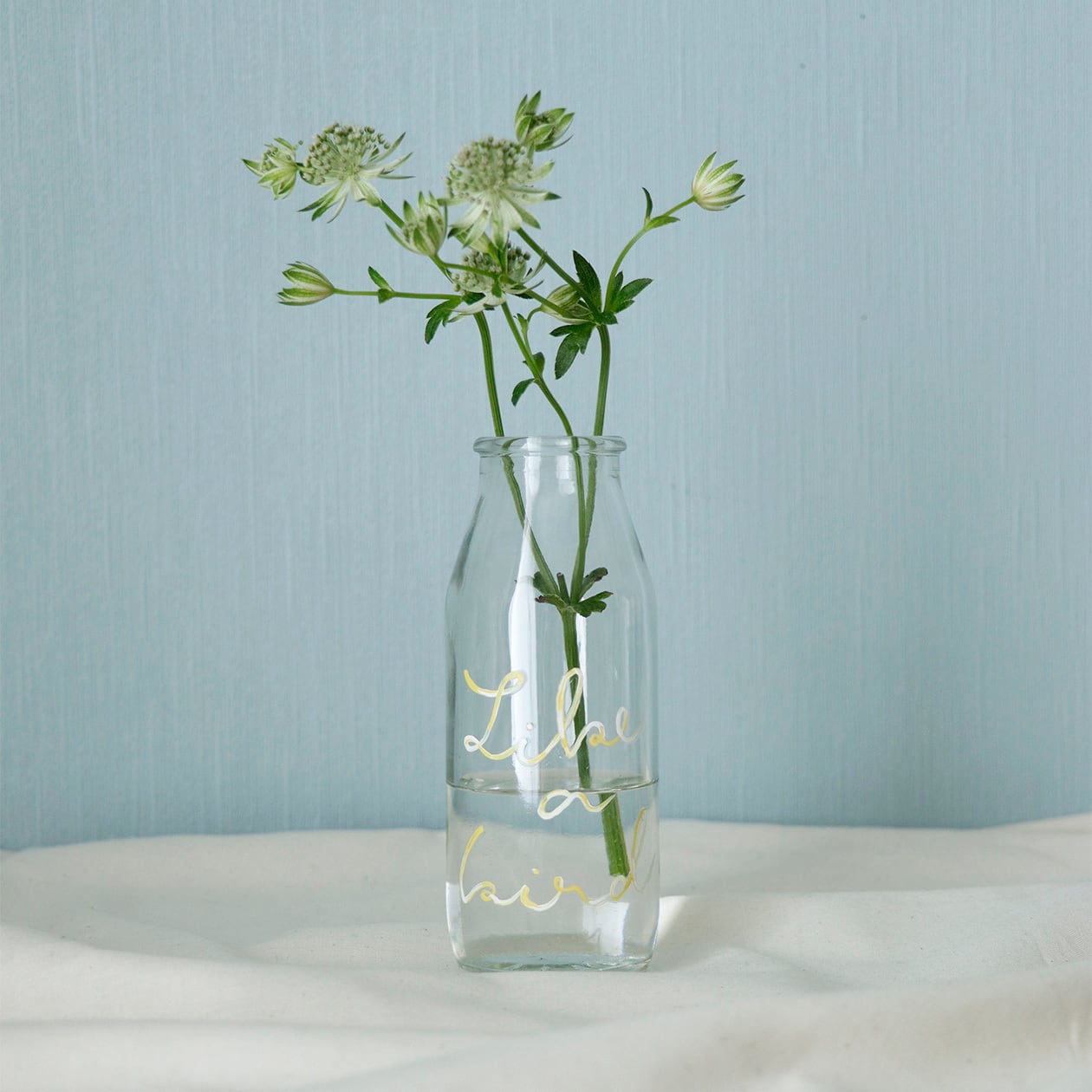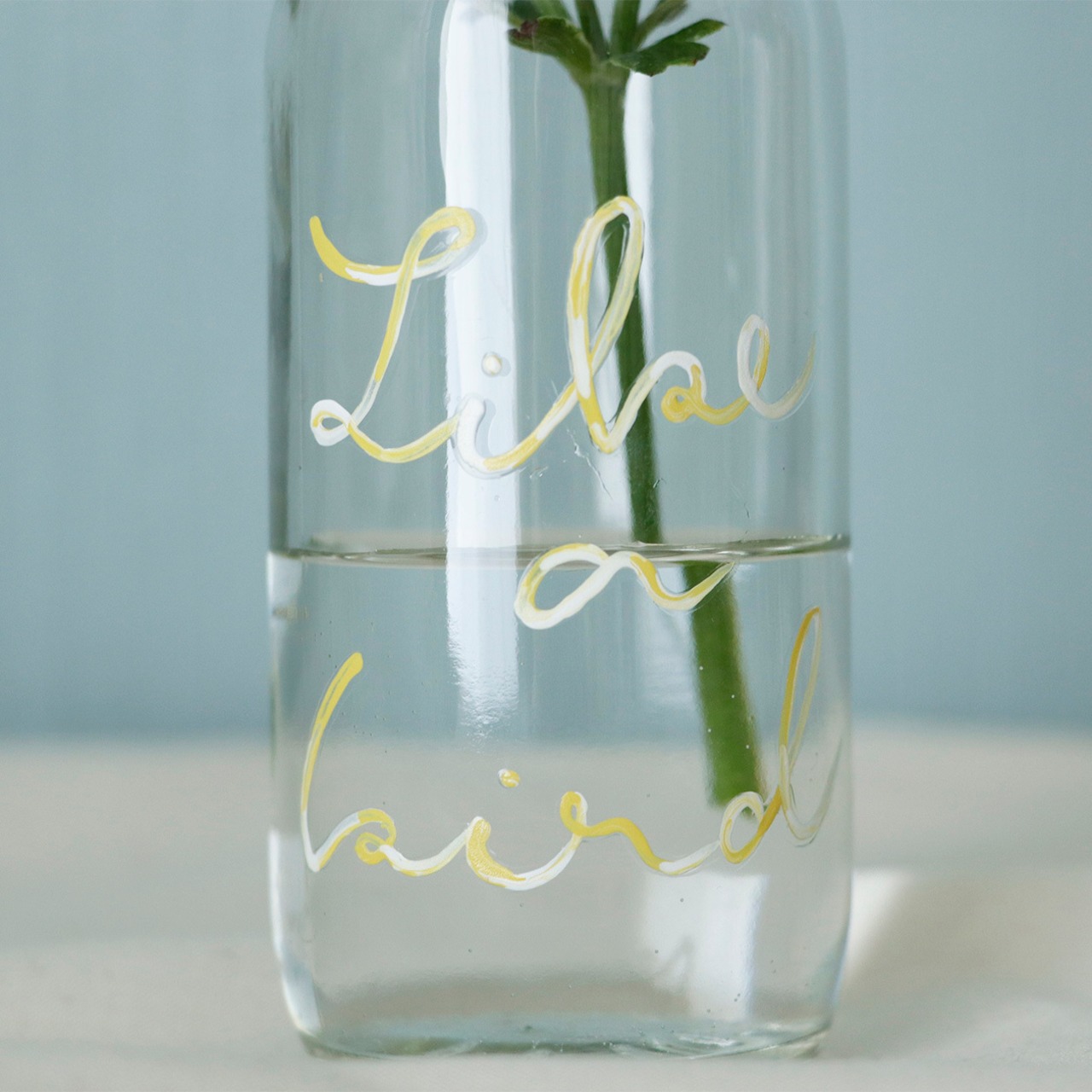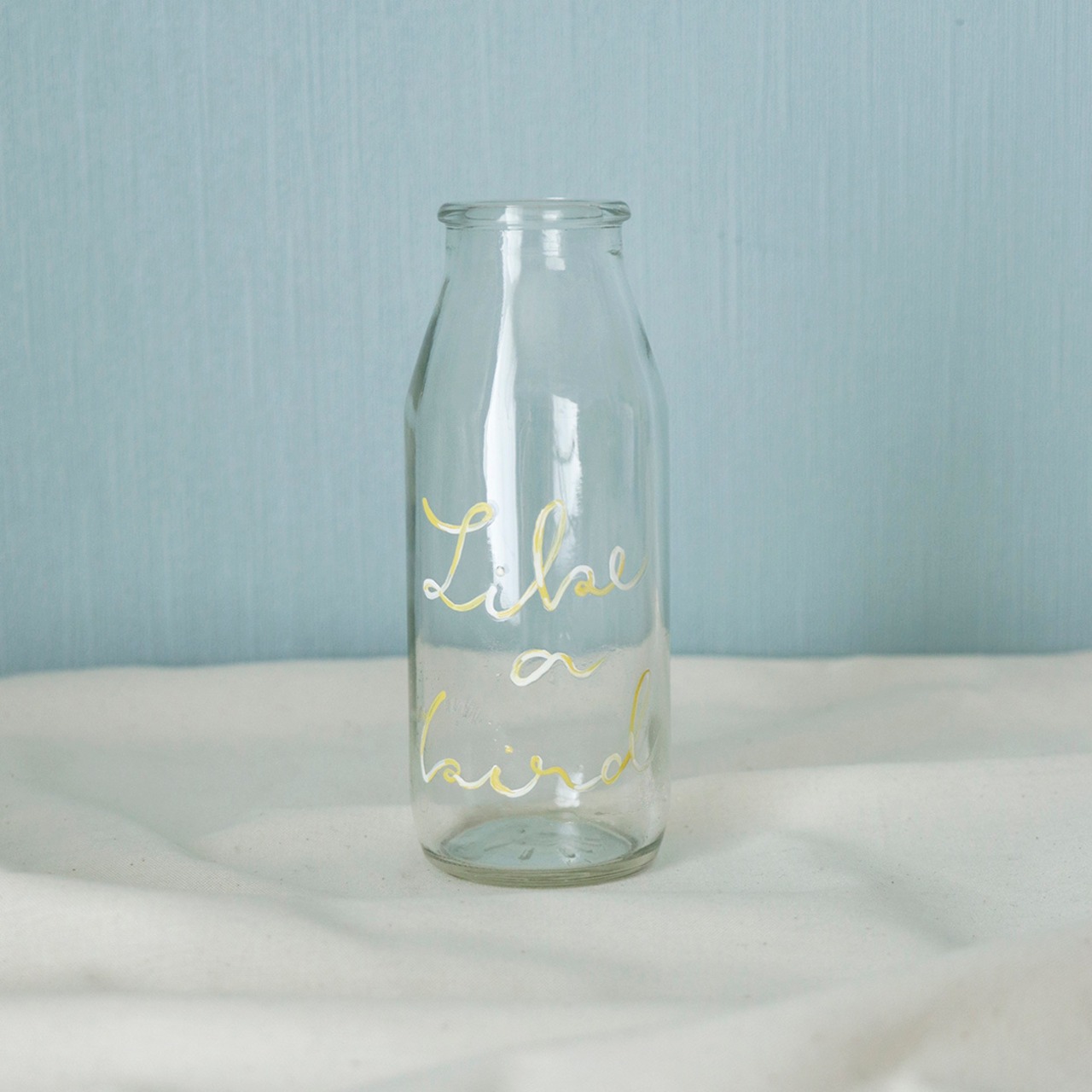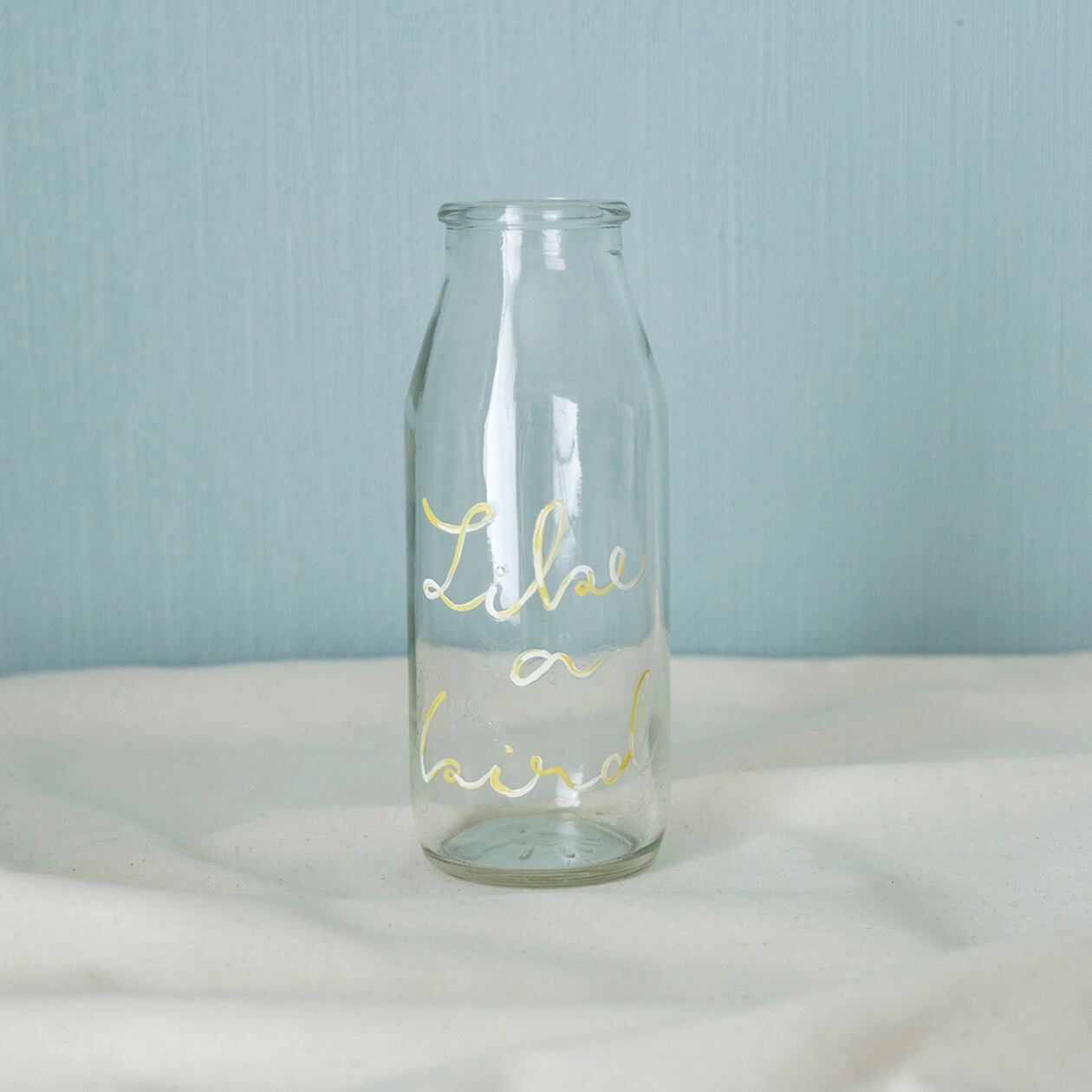
【BOTTLE PAINT ART】Like a bird
Like a bird
鳥のように楽々と
肩の力を抜いて、鳥のように羽ばたいていきたい
そんなイメージの筆記体にしました。
黄色と白のマーブルな文字が可愛い!
花瓶として、そのまま飾ってディスプレイとしても◎(食用はおすすめしません)
光が入るとこに置くと、瓶の色とともに文字も影になって素敵ですよ!!